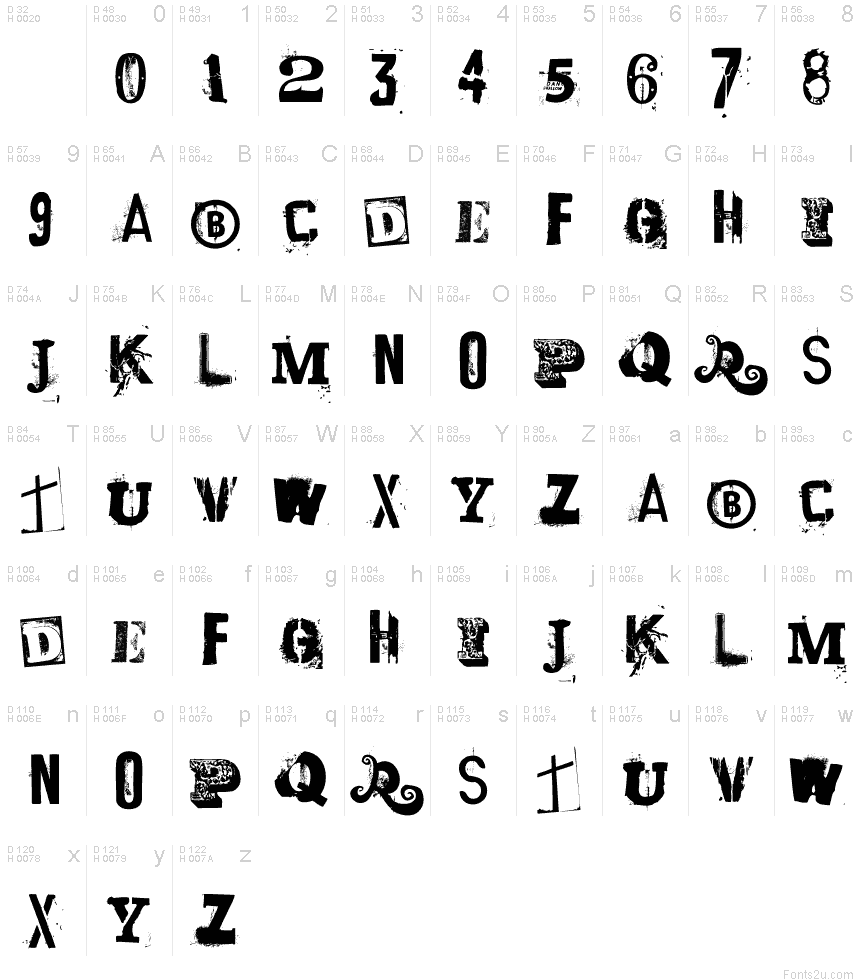
Laundromat 1967 od Gyomsegs to darmowy krój displayowy w stylu grunge, oparty wyłącznie na wielkich literach, który przywodzi na myśl zniszczone szyldy i odbitki na starym papierze. Litery łączą w sobie surowe krawędzie, ślady zużycia i lekko nieregularne kształty, dzięki czemu font przypomina zestaw liter wyciągniętych ze starych plakatów, a nie wygładzony, geometryczny projekt.
Idealnie pasuje do ulotek muzycznych, okładek zinów, brandingów w stylu retro, kart tytułowych i nagłówków, gdzie ta surowa, „ręcznie” składana tekstura gra pierwsze skrzypce. Jako darmowy font świetnie sprawdzi się też w monogramach czy krótkich hasłach, ponieważ masywne wielkie litery i nierównomierne wykończenie nadają nawet pojedynczym znakom wygląd czegoś, co zostało wydrukowane, naklejone i nadszarpnięte zębem czasu.